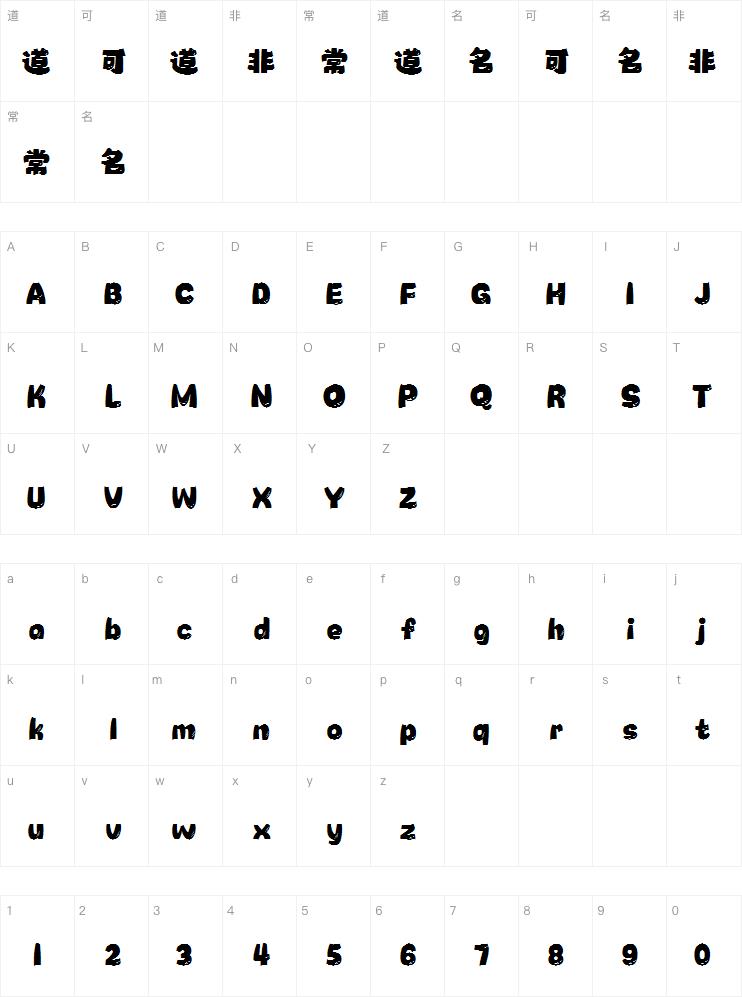
字魂卡皮巴拉体
字魂卡皮巴拉
字魂卡皮巴拉体从水豚的神态中提取灵感,字形宽扁憨粗,采用圆润、稚拙的笔触,复刻TATA给人的可爱联想。字体笔画上,设计了微翘和高光的细节,增添了活泼和生动之感。这款字体十分具有视觉感染力,在儿童、母婴、萌宠、餐饮等商业领域能得到广泛的应用。不论是产品包装、品牌宣传或是周边设计,这款字体都带来丰富的排版装饰效果。
字魂卡皮巴拉体